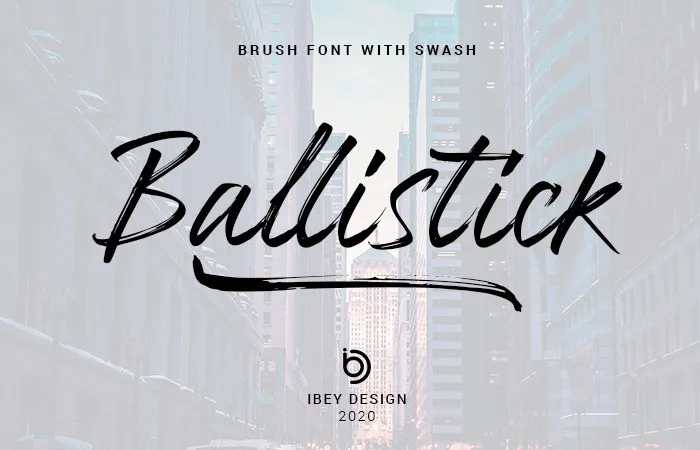
A fonte Ballistick é ideal para quem busca uma sensação autêntica de arte livre. Esta script brush font foi criada a partir de traços de pincel úmidos trazidos à vida sobre papel, um método que captura verdadeiramente o esforço e o poder da mão humana na criação artística. Desenvolvida por ibeydesign, Ballistick é perfeita para diversos usos, como fotografias, selos de marca, posts nas redes sociais, anúncios, logotipos e identidades, convites, design de produtos, etiquetas, papelaria, celebrações casamenteiras, embalagens de produto e eventos especiais. Suas linhas fluidas e a textura única tornam-a ideal para destacar seus projetos com um toque autêntico do pincel, seja em documentos, sites ou materiais impressos. Seja você designer gráfico, editor de fotos ou criador de redes sociais, Ballistick é sua nova escolha para adicionar uma nota pessoal e distintiva aos seus trabalhos.